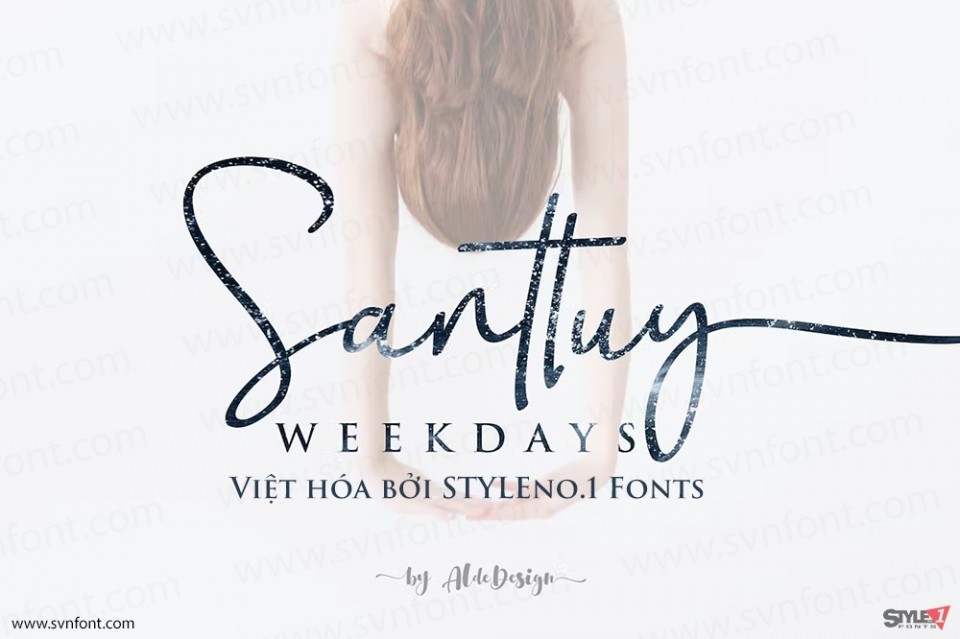
Font việt hóa SVN Weekdays Santtuy
Giới thiệu về Font việt hóa SVN Weekdays Santtuy
Trong thiết kế đồ họa hiện đại, việc lựa chọn một bộ font phù hợp đóng vai trò quyết định đến thẩm mỹ của sản phẩm. Font việt hóa SVN Weekdays Santtuy là một trong những lựa chọn hàng đầu cho các nhà thiết kế yêu thích phong cách viết tay mềm mại và tự nhiên. Được biết đến như một mẫu Font Miễn Phí ấn tượng, bộ chữ này mang lại cảm giác gần gũi nhưng không kém phần sang trọng. Với khả năng tương thích cao, đây là công cụ đắc lực giúp bạn tạo nên những tác phẩm nghệ thuật chữ độc đáo trên các nền tảng thiết kế phổ biến hiện nay.
Đặc điểm nổi bật của Font việt hóa SVN Weekdays Santtuy
Điểm thu hút nhất của bộ font này chính là những đường nét uyển chuyển, mô phỏng chân thực nét bút mực trên giấy. Từng ký tự được chăm chút tỉ mỉ với độ đậm nhạt tinh tế, giúp văn bản trở nên sống động hơn. Đặc biệt, phiên bản việt hóa đã được tối ưu hóa hoàn toàn hệ thống dấu tiếng Việt, đảm bảo không bị lỗi font khi gõ. Điều này rất quan trọng đối với cộng đồng thiết kế tại Việt Nam khi muốn thể hiện nội dung một cách trọn vẹn và đẹp mắt nhất.
Ứng dụng thực tế của Font việt hóa SVN Weekdays Santtuy
Thiết kế truyền thông và giáo dục
Nhờ vẻ ngoài thanh thoát, bộ font này cực kỳ phù hợp để làm thiệp mời, bìa sách hoặc các dự án sáng tạo trong trường học. Các bạn học sinh có thể dùng nó để trang trí bài thuyết trình hoặc làm tiêu đề cho các ấn phẩm nội bộ. Ngoài ra, các nhãn hàng cũng thường xuyên sử dụng nó cho các chiến dịch marketing đòi hỏi sự nữ tính và nhẹ nhàng.
Kết luận về Font việt hóa SVN Weekdays Santtuy